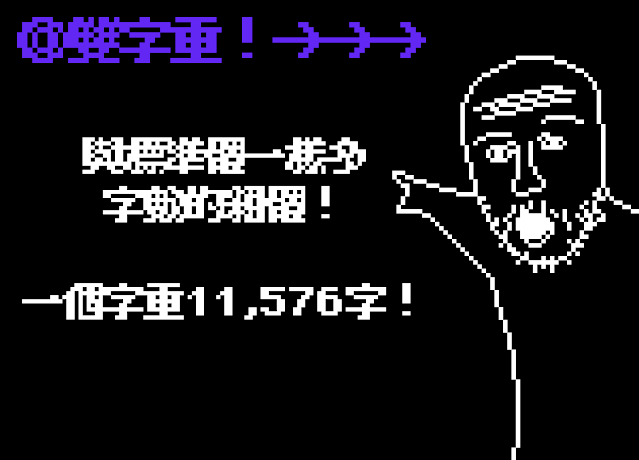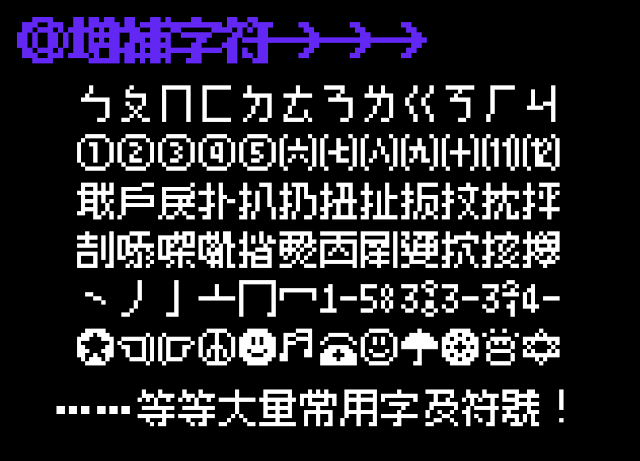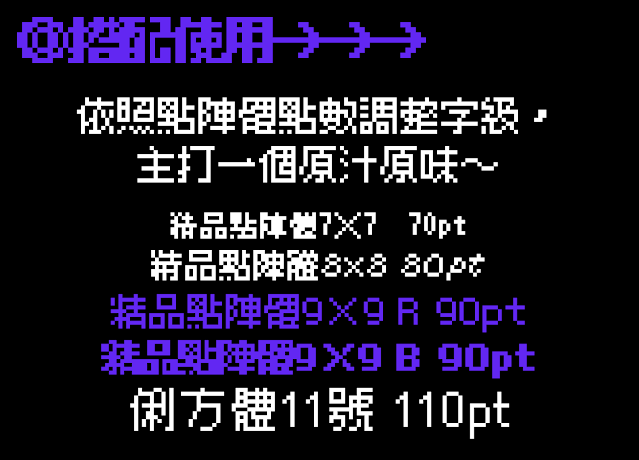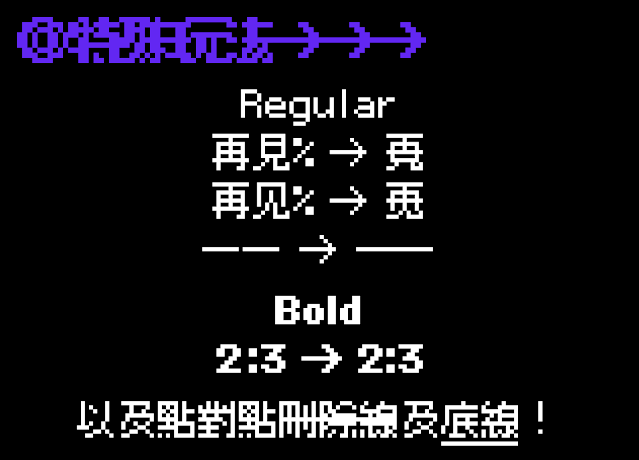
《精品点阵体9×9 (BoutiqueBitmap9x9) 》家族是一款基于M+ BITMAP FONTS及ベストテン(BestTen-DOT)改作的字型,目的为适合在繁体中文环境中使用。我们改正了一些标点符号、日本习惯写法、增加大量字符与Opentype特性——包括颜文字用符号、简体中文、直排特性等——使字型使用更方便!
这是一款带有极强烈的点阵风格的字型,非常适合用在像素书、遊戏相关主题等等。
另外《精品點陣體7×7》也同时合并了《观致》的字符,目前可支援14,943个字。